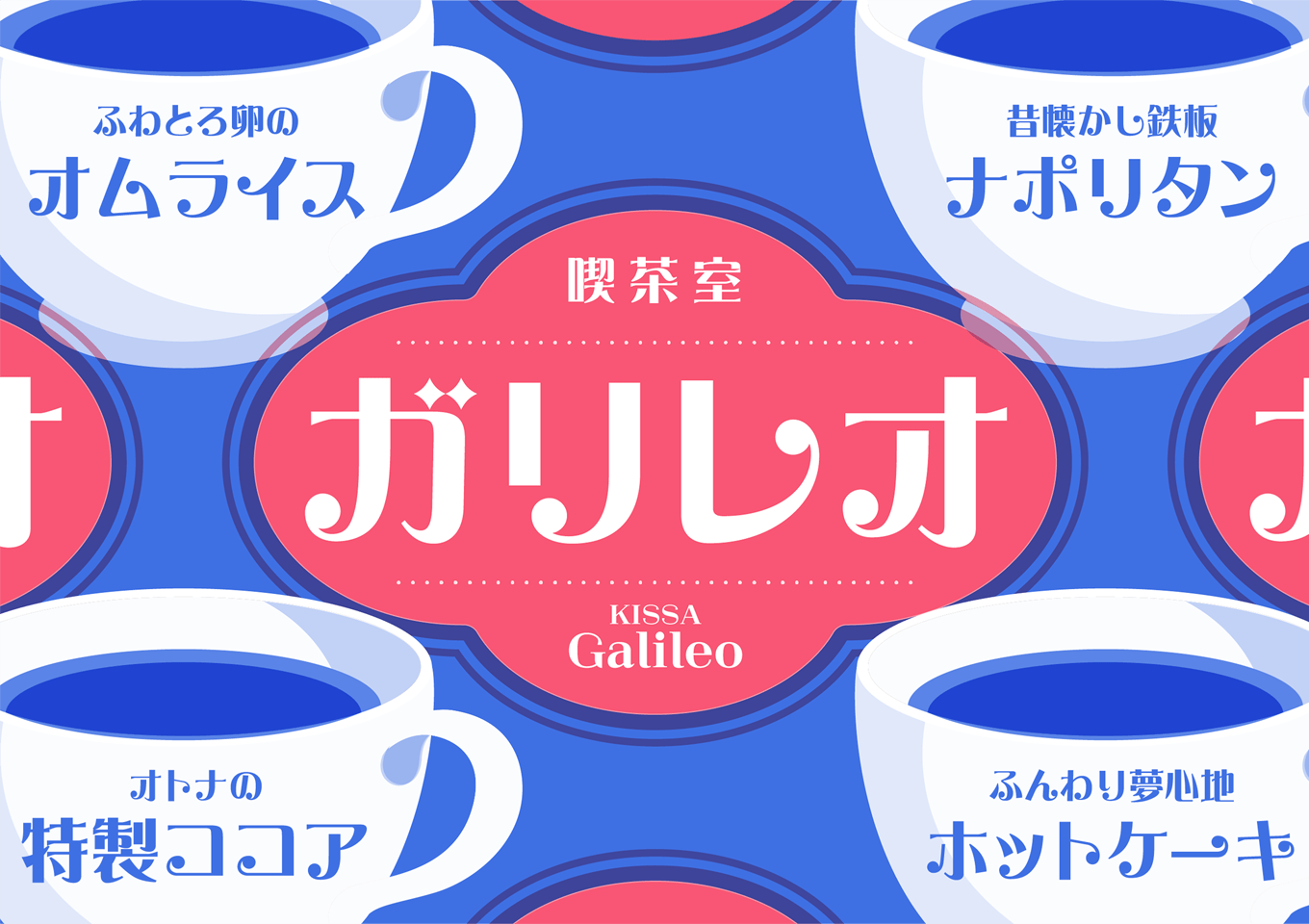
やや低めの重心をもつスクエアな骨格の漢字に、きらびやかな印象のかなを合わせた、ハイコントラストなデザイン書体です。「翠流ネオロマン」のかなのデザインをベースに、エレメントの先端や濁点部分の装飾を加えることで華やかな印象がプラスされています。広告や動画テロップなどで、ロマンチックな世界観を表現する際に最適な書体です。なお本書体はモリサワで制作したかな・英数字に、Arphic Typesの「AR浪漫明朝体」の漢字を組み合わせています。